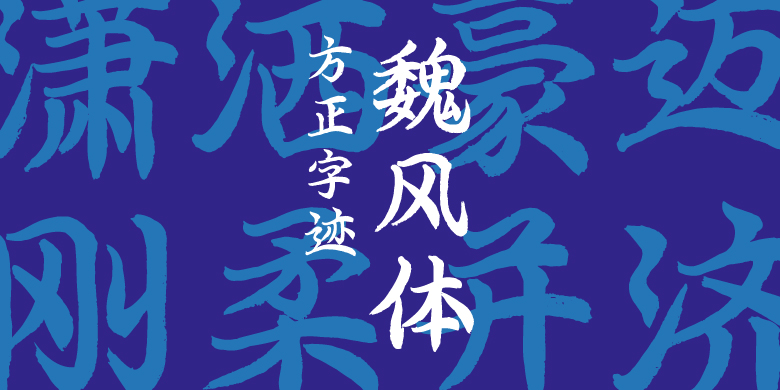
方正字迹-魏风体
夏清泉
常规书写·毛笔
灵感来自《崔敬邕墓志》等魏碑,蕴含了写经体及行书笔意。字型飘逸,动静结合,刚柔相济。横画左尖右圆,竖画钉头起笔中细下粗,撇画钉头起笔,捺画为反捺,钩画出长锋,折画顿挫骨感。笔画或粘连,或隔断、或牵丝。重心偏上偏右,左放右收,左轻右重,上紧下松。适用场景:艺术、体育、古籍、怀旧、 招牌、标题等。